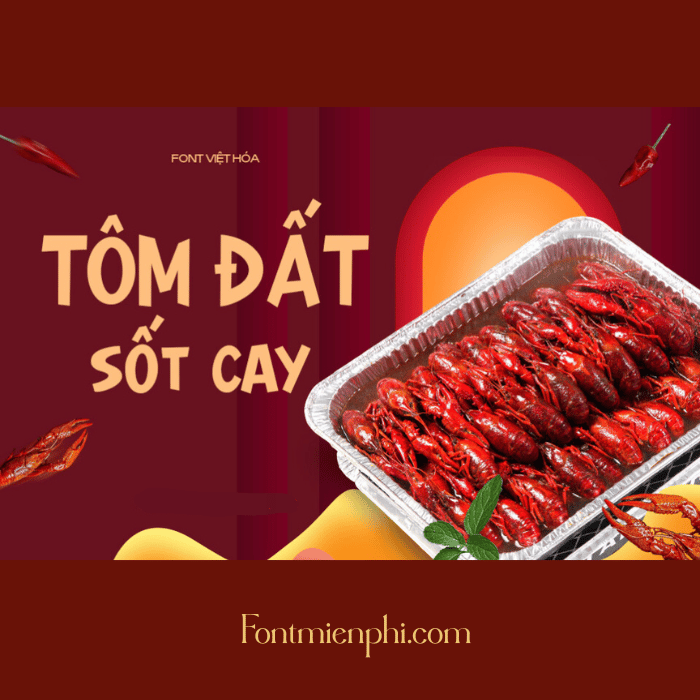
Giới thiệu về bộ Font Việt hóa 1FTV VIP Komika
Trong thế giới thiết kế đồ họa dành cho giáo dục và giải trí, việc tìm kiếm một bộ phông chữ vừa mang tính vui nhộn vừa hỗ trợ đầy đủ tiếng Việt là điều vô cùng quan trọng. Font Việt hóa 1FTV VIP Komika chính là giải pháp hoàn hảo cho những ai đang tìm kiếm phong cách Comic độc đáo. Đây là một mẫu Font Miễn Phí được tinh chỉnh kỹ lưỡng về dấu câu, giúp các bạn học sinh và thầy cô giáo dễ dàng tạo ra những bài giảng sinh động hoặc các bộ truyện tranh tự làm hấp dẫn. Với đường nét dày dặn và bố cục rõ ràng, bộ font này đảm bảo tính thẩm mỹ cao trên mọi nền tảng hiển thị.
Ưu điểm nổi bật của Font Việt hóa 1FTV VIP Komika
Phong cách thiết kế đậm chất Comic
Font Việt hóa 1FTV VIP Komika mô phỏng hoàn hảo các kiểu chữ trong truyện tranh phương Tây. Sự biến hóa linh hoạt giữa các nét đậm nhạt giúp nội dung trở nên lôi cuốn, giảm bớt sự khô khan cho các văn bản thông thường. Điều này cực kỳ phù hợp để làm tiêu đề bài học hoặc chú thích ảnh.
Khả năng tương thích và ứng dụng đa dạng
Để tận dụng tối đa vẻ đẹp của bộ font này, bạn nên kết hợp với các tông màu rực rỡ và đổ bóng nhẹ để tạo hiệu ứng 3D. Đây là lựa chọn hàng đầu cho các dự án thiết kế poster trường học, thiệp mời hoặc làm phụ đề video clip vui nhộn. Đừng quên kiểm tra kỹ các khoảng cách chữ để nội dung luôn dễ đọc nhất. Nếu bạn đang tìm kiếm nguồn tài nguyên chất lượng, hãy truy cập ngay Font Miễn Phí, Font Việt Hóa, Font Việt hóa 1FTV VIP Komika để sở hữu bộ gõ tuyệt vời này cho bộ sưu tập cá nhân của mình.